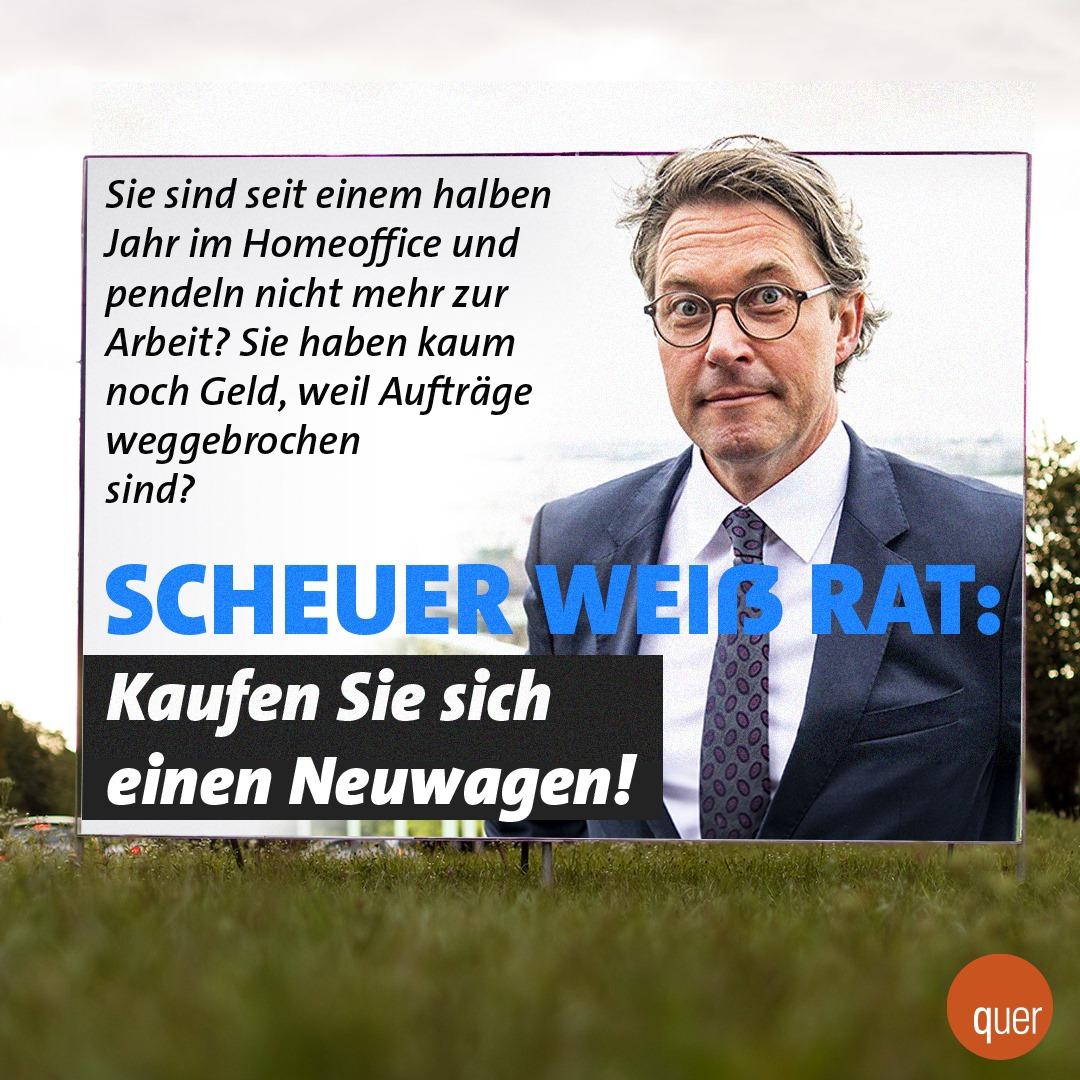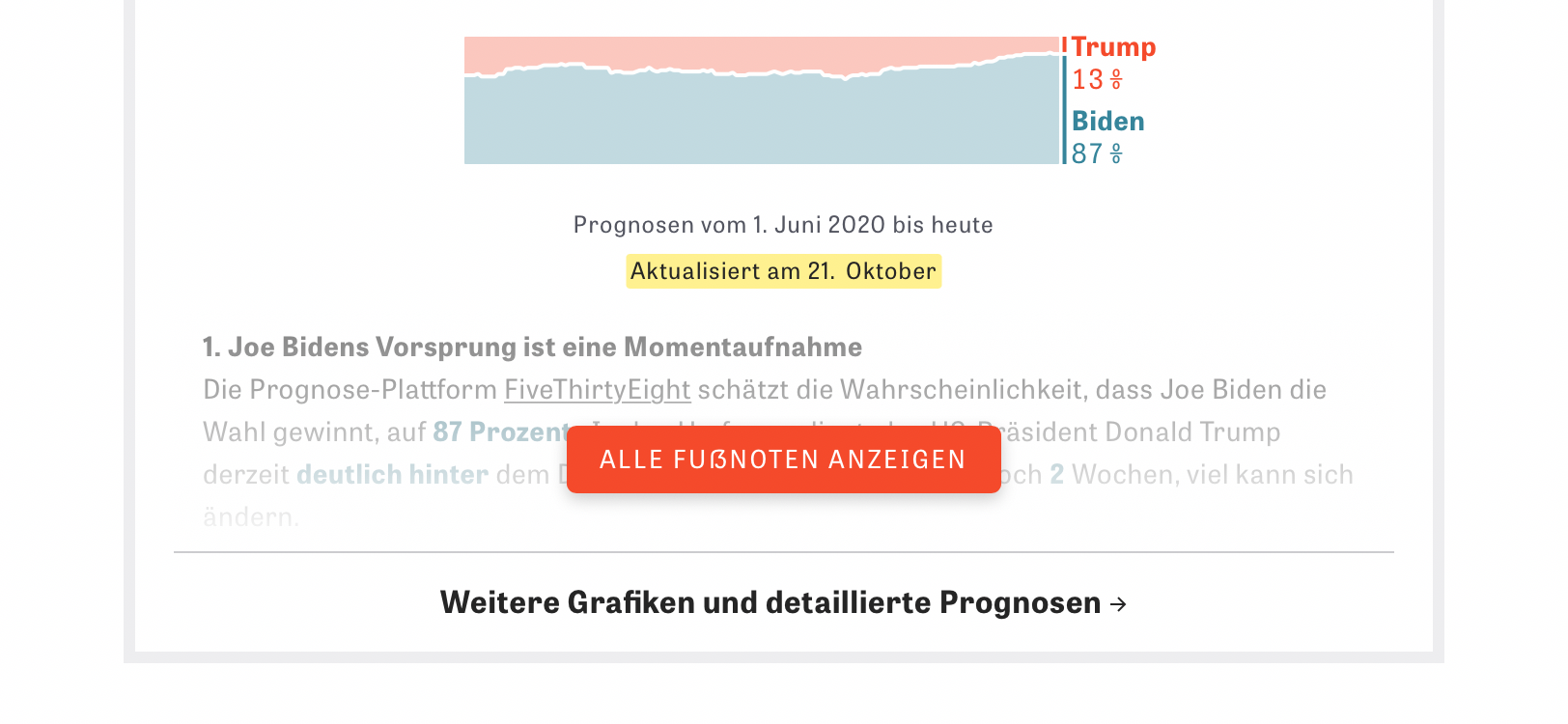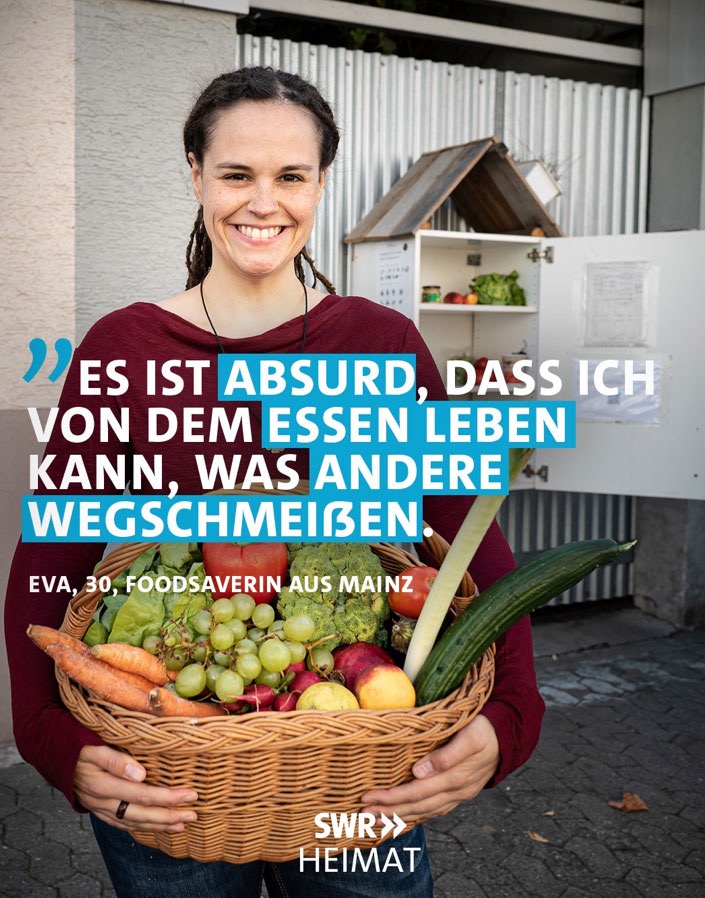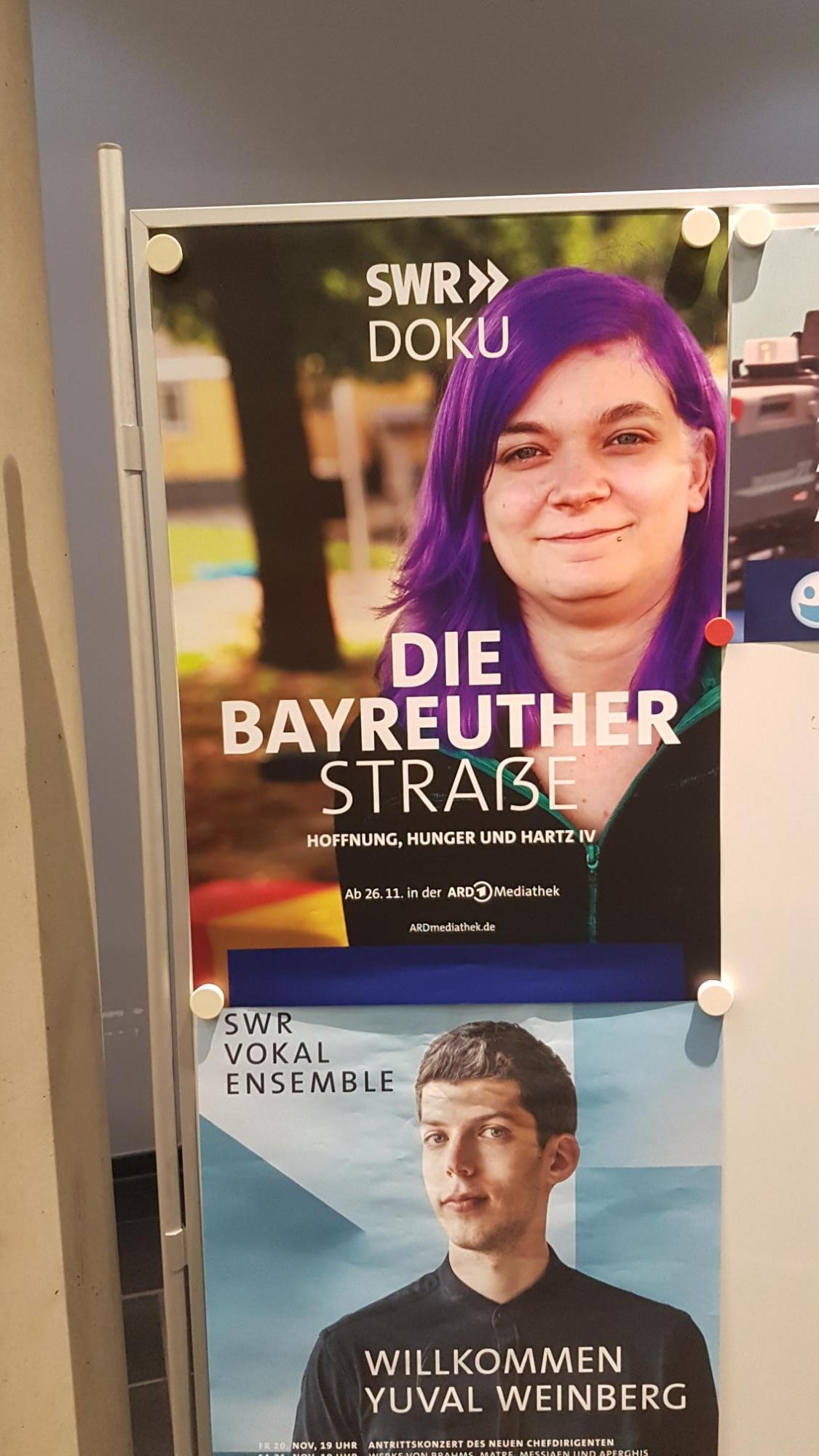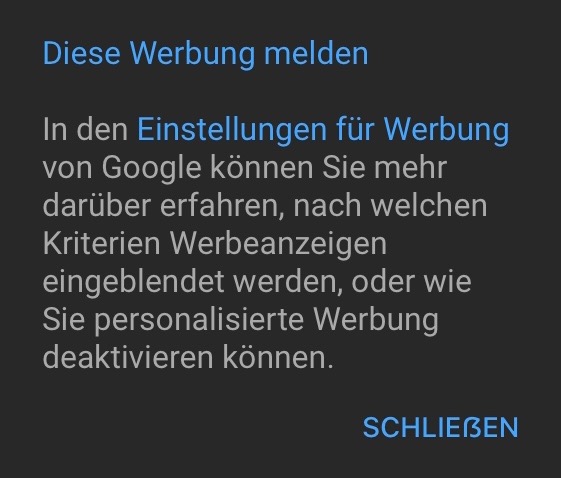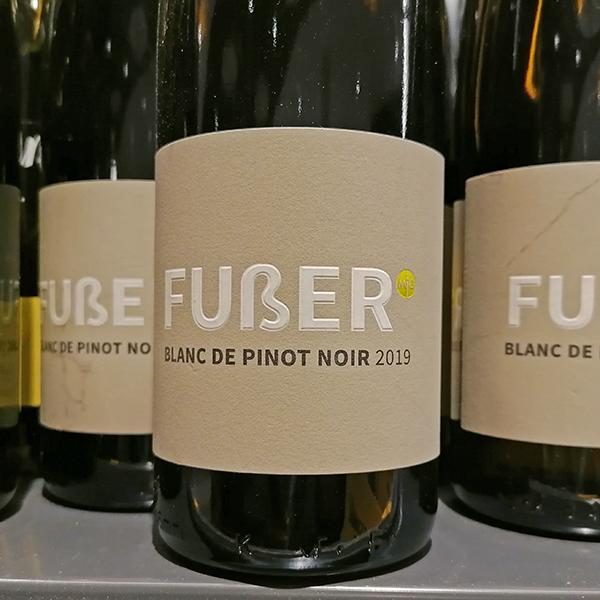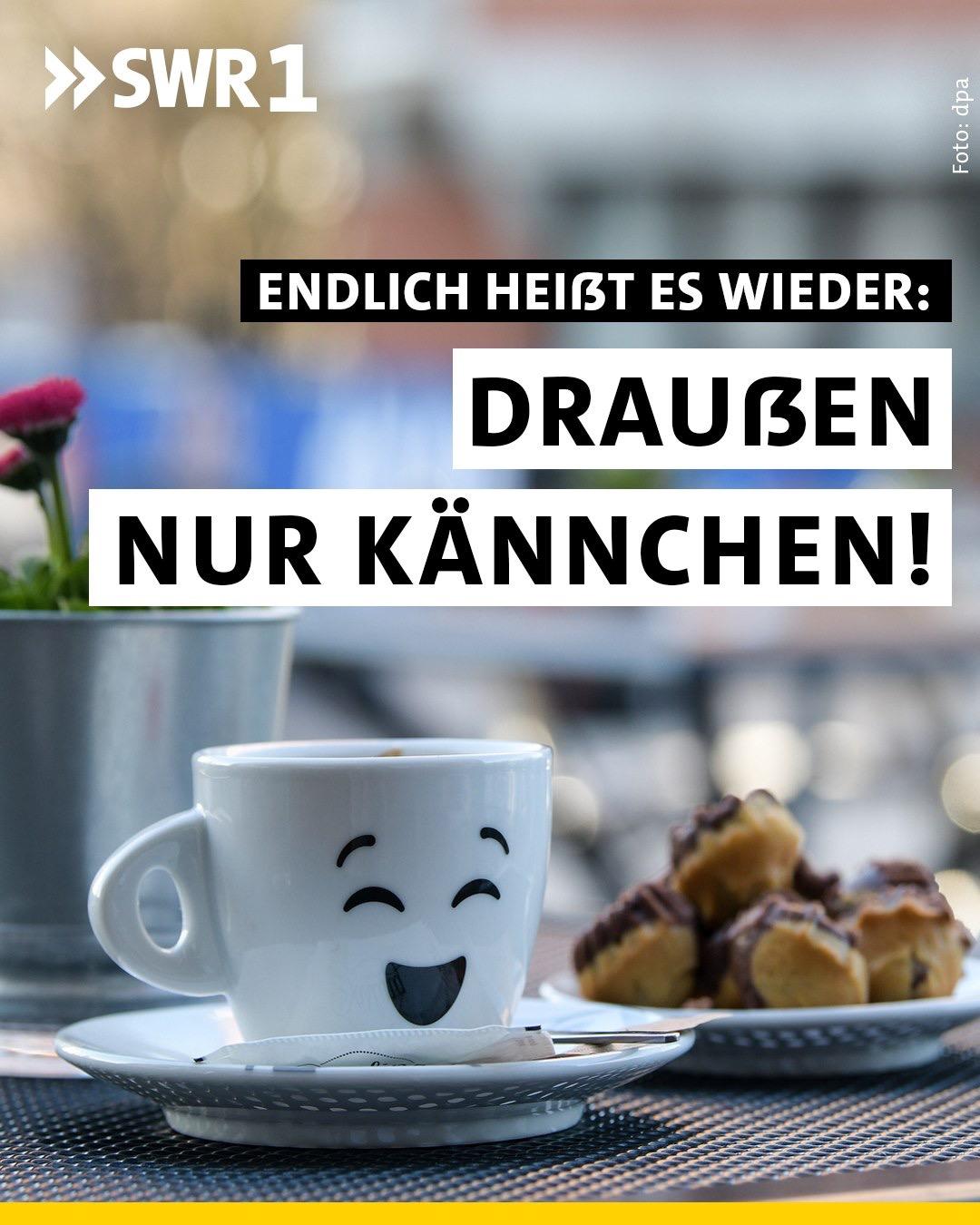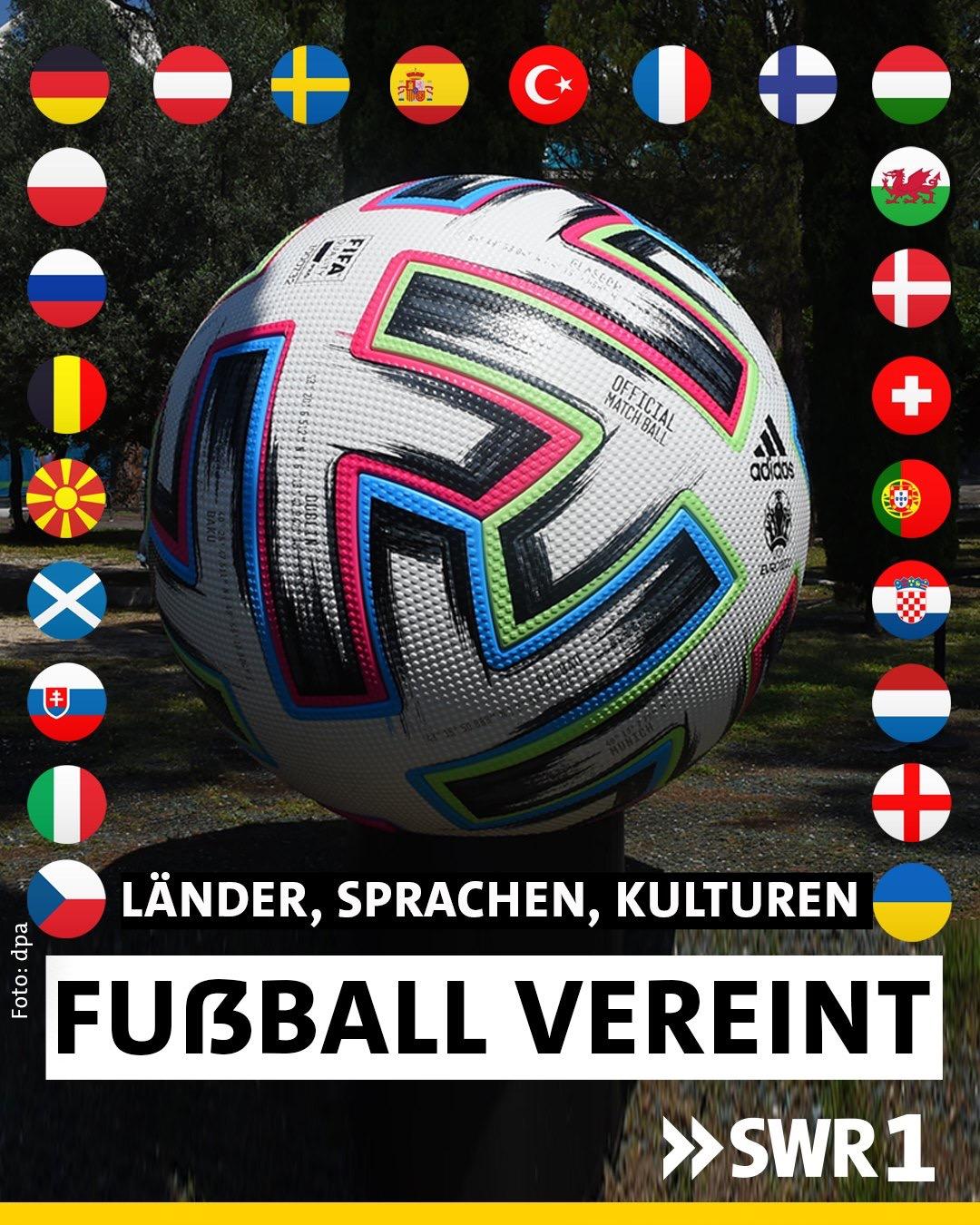
Der Leser »Martin-x6X_kryZR« schreibt heute bei Spiegel online: »Lieber Herr Lobo. Ein kleiner Hinweis. Sie übersetzten Trumps Twitternachricht mit "GROSSER SIEG". Es gibt in der zwsichenzeit das große ẞ, das genau für solche Zwecke eingeführt wurde. I diesem Sinne: "DAS GROẞE ẞ IST GROẞARTIG!«
irgendwie passt das auch in den Stil
In den Stil der Demo? Dass sich eine Minderheit aufbläht ohne formal oder inhaltlich nachvollziehbare Grundlage? Einfach sich breit machen ohne Rücksicht auf die Typen vor und hinter mir?
In den Stil der Demo?
Nein, in den Stil der Schrift. Findest Du das Versal-Eszett (wenn es denn eines ist, da bin ich mir nicht so sicher) "aufgebläht und ohne formal nachvollziehbare Grundlage"? Oder war das nur ein esoterischer ( 😉 aber nachvollziebarer) Kommentar?
wenn es denn eines ist
Ich würde auch meinen, dass es ein kleines (aber irgendwie in die Breite gezogenes?) ist …
Nein, in den Stil der Schrift. Findest Du das Versal-Eszett (wenn es denn eines ist, da bin ich mir nicht so sicher) "aufgebläht und ohne formal nachvollziehbare Grundlage"?
Wenn ich mir die anderen Buchstaben zur Grundlage nehme , schon. Absoluter Außenseiter.
Gestern im Supermarkt am Weinregal:
Die Schrift ist mit weißer Farbe auf gefärbtem Papier gedruckt und zusätzlich erhaben. Lack oder Prägung konnte ich im Supermarkt nicht feststellen. Aber eigentlich geht es ja auch um den Buchstaben.
Dient für meine Begriffe eher als Negativ-Beispiel, oder? Dieses Exemplar sieht nun gerade gar nicht versal aus, sondern wie der Kleinbuchstabe, der auf Zeilenhöhe gequetscht wurde. 🤷‍♂️
Das denke ich auch. Hier kann man es noch bessersehen.
Dabei hätte ein echtes Versal-Eszett auf einem so aufgeräumten Weinetikett eine großartige Wirkung.
Wobei Zurichtung/Kerning nicht ganz stimmig ist beim VE … oder irre ich mich 🤔
Mir ist das Piratenplakat beim Wochenendspaziergang als Einziges positiv aufgefallen, da alle anderen sich ums große Eszett irgendwie herumzumogeln scheinen.